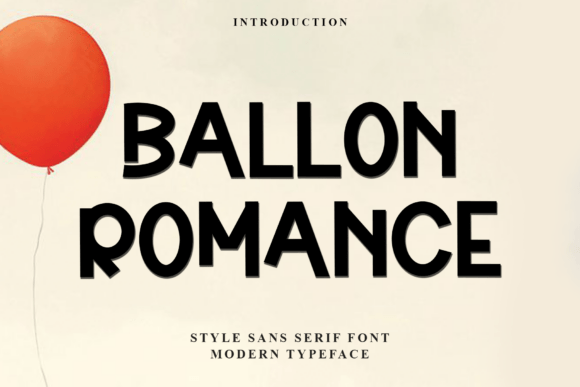
Ballon Romance
Ballon Romance gibi yüksek kaliteli varlıklar arıyorsanız, bu premium paket yaratıcı projeleriniz için harika bir seçimdir.
İster İsteğe Bağlı Baskı (POD) ürünleri, ister düğün davetiyeleri veya sosyal medya grafikleri oluşturuyor olun, Ballon Romance ideal bir uyumdur.